Manutius, Aldus
Italienischer Humanist, Verleger und Typograf. Geboren um 1449 in Bassiano, einem Dorf in der Provinz Latina in der italienischen Region Latium, etwa 60 Kilometer südöstlich von Rom. Aldus Manutius (der Ältere) war der bedeutendste Vertreter und Gründer der venezianischen Typografenfamilie Manuzzi (Mannucci), dessen knapp 900 Werke mit dem Gattungsbegriff »Aldinen« charakterisiert werden. Alternative Schreibweisen seines Namens: Teobaldo Manucci, Teobaldo Mannucci, Aldo Pio Manuzio, Amius Manutius und Aldus Pius Manutius Romanus.
Aldus Manutius gilt als wichtiger Wegbereiter für die Wiederbelebung (Renaissance) antiker Literatur, die mit dem Fall des Byzantinischen Reiches (Oströmisches Reich) durch emigrierte byzantinische Gelehrte nach Europa gelangte und die den kulturellen Umbruch vom Mittelalter zur Neuzeit einleitete. »Die seltene Vereinigung von Gelehrsamkeit, Schönheitssinn und verlegerischer Initiative macht Manutius zum größten Drucker seiner Zeit.« 1)
Aldus Manutius studierte antike Philologie und Latein in Rom bei Gasparino da Verona (Caspar von Verona, o.A.) 2) und Griechisch in Ferrara bei Guarino da Verona (Baptista Guarinus aus Verona, 1374–1460). Danach lebte er rund zwei Jahre mit seinem Kommilitonen und Freund Giovanni Pico (Giovanni Pico Conte della Mirandola, 1463–1494) 3) in Mirandola, um seine Studien in altgriechischer Literatur zu vertiefen. In seiner Mirandolaner Zeit wohnte er mit dem Griechen Emanuel Adramyttenus zusammen, der aus Kreta flüchtete und der ihm dabei half, seine Sprachgewandtheit in Griechisch zu vertiefen. 4)
Über Giovanni Pico lernte Aldus Manutius auch dessen Neffen Alberto (Pio di Savoia, 1475–1531) und Lionello (o.A.–1535) Pio, die Fürsten von Carpi kennen. Auf Picos Initiative hin wurde Manutius ihr Tutor und Lehrer. 1485/86 siedelte Manutius nach Carpi (Emilia-Romagna, heute Provinz Modena) in das Haus der verwitweten Fürstin Catharina von Carpi (Caterina Pico della Mirandola, 1454–1501) über, wo er auch ihre Söhne – Alberto und Lionello – unterrichtete, die ihm zeitlebens eng verbunden blieben.
Um 1490, vielleicht auch schon 1488 oder 1489, zog Manutius von Carpi nach Venedig, wo er Vorlesungen über alte Autoren hielt und hauptsächlich die »Deutsche Kunst«, also das Drucken lernte. 5) 6) Manutius lebte zunächst im Bezirk San Polo in der Pfarrgemeinde der »Chiesa di Sant’Agostin«, später im Bezirk San Marco in der Pfarrei der »Chiesa di San Paternian«, wo auch der wohlhabende Typografen Andrea Torresani di Asolo (1451–1528/1529) als Mitinhaber und Leiter der Offizin »Johannes de Colonia, Nicolaus Jenson et socii« arbeitete, mit dem er zusammen vermutlich ab 1495 Bücher druckte und dessen Tochter er 1503 heiratete.
In Torresanis Besitz befanden sich möglicherweise seit 1475 auch die griechischen Drucktypen des französischen Kupferstechers und Typografen Nicolas Jenson (um 1420–1480), der im Gefolge der deutschen Prototypografen Arnold Pannartz (o.A.–um 1476), Conrad Sweynheym (o.A.–um 1474/1477) 1468 nach Venedig kam, um dort ab 1468/1469 bei den Gebrüdern Johannes (o.A.–1469/1470) und Wendelin (o.A.–1477) von Speyer (Giovanni and Vendelino da Spira) zu arbeiten. 7) Es ist anzunehmen, dass diese griechische Drucktypen aus dem Besitz von Jenson – die vermutlich um 1476 von dem Typografen Dionysius Paravisinus (o.A.) in Mailand geschnitten wurden – 8) wesentlich die Letternarchitektur (Typometrie) der aldinischen kursiven Drucktypen beeinflusste. 9)
Mit der finanzieller Unterstützung der Fürsten von Carpi 10) gründete Aldus Manutius 1494 die Officina »Aldina« in Venedig (mögliche Adresse: Casa di M. Aldo apresso Sancto Augustino doue se stampe), die sich neben Prachtdrucken auf Pergament besonders der textkritischen Edition von Klassikern der griechischen und römischen Literatur widmete, die überwiegend aus Schenkungen des Dichters und Geschichtsschreiber Francesco Petrarca (1304 –1374) sowie dem byzantinischen Theologen, Humanist und Kardinal Johannes Bessarion (um 1399/1408–1472) an die Biblioteca Marciana (heute Biblioteca Nazionale Marciana). 11)
Ab 1495 veröffentlichte Aldus Manutius die ersten Drucke in griechischen Lettern (Drucktypen). Sein erstes Werk war ein Nachdruck der griechischen Grammatik »Erotemata« des Byzantiners Konstantinos Laskaris aus Konstantinopel (um 1433/1434–1501), die 1476 erstmals von Dionysius Paravisinus in Mailand gedruckt wurde.
Diese höchst erfolgreichen Ausgaben erschienen auch in Form des preiswerten und handlichen Oktavformats (8°), 12) welches man als Prototyp unseres heutigen klassischen Taschenbuchformats bezeichnen kann. Darunter Schriften von Aristoteles (384 v.Chr.–322 v.Chr.) Thukydides (vor 454 v.Chr.–399/396 v.Chr.), Sophokles (497/496 v.Chr.–406/405 v.Chr.), Herodot (um 490/480 v.Chr.–um 424 v.Chr.) und Xenophon (430/425 v.Chr.–nach 355 v.Chr.).
Manutius war der erste Typograf, der konsequent dem philologischen Regelkanon von Grammatik, Orthographie und systematischer Groß- und Kleinschreibung folgte.
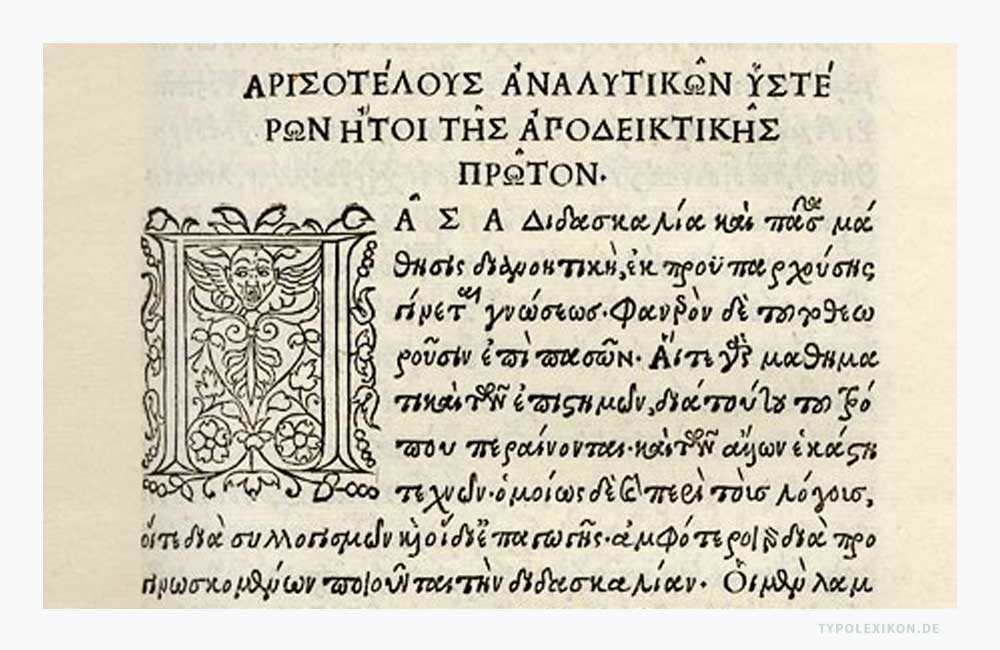
Gemeinsam mit anderen Humanisten, unter ihnen (der spätere Kardinal) Pietro Bembo (1470–1547), der auch die Klassikereditionen der Offizin Manutius textkritisch redigiert hatte, bildete Aldus Manutius die sogenannte »Neacademia«, eine wissenschaftliche Gesellschaft, aus der später die »Accademia della Fama« hervorging, einer der Keimzellen des Humanismus und der Wiederentdeckung der Antike in der Renaissance.
Als Typograf entwickelte Aldus Manutius zwischen 1495 und 1502 mit seinem talentierten bologneser Schriftgießer und Stempelschneide Francesco Griffo (Francesco da Bologna, 1450–1518) 1495 die ersten kursiven griechischen Drucktypen.
| ↑15 | Tipp: Das Aldusblatt in unterschiedlichen Varianten ist in zahlreichen Fonts als Sonderzeichen enthalten, beispielsweise bei der »ITC Zapf Dingbats« von Hermann Zapf (1918—2015) oder der »Minion Pro« von Robert Slimbach (*1992). |